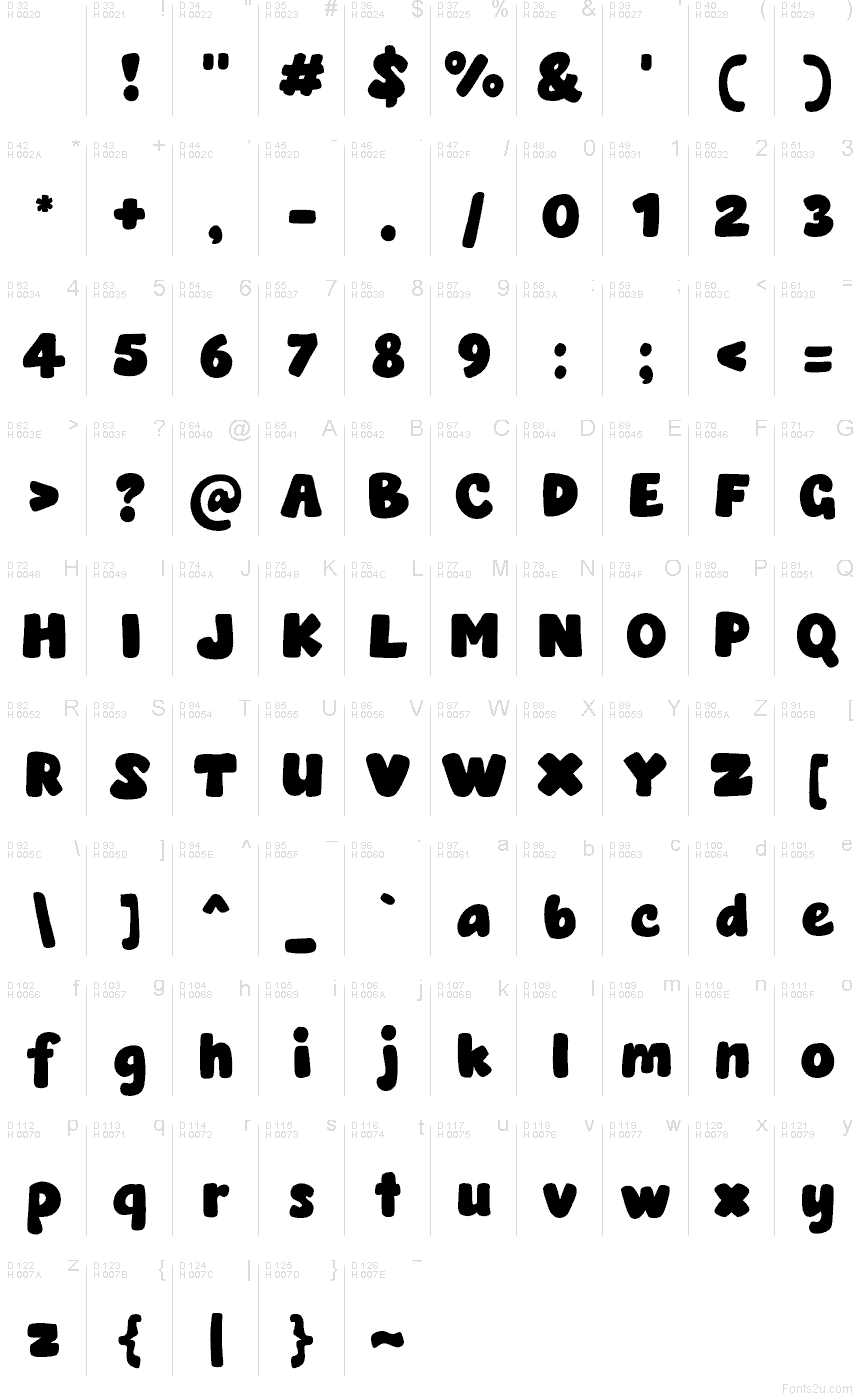
Marshi Sans
Marshi Sans od Origin Type je bezplatné komiksové písmo, ktoré sa vyznačuje zaoblenými tvarmi pripomínajúcimi bubliny a mäkkými rohmi, vďaka čomu pôsobí ako ručne kreslené a má priateľský rytmus. Písmená sú usporiadané vzdušne a neformálne a široké krivky zaisťujú, že celý vzhľad zostáva uvoľnený a prístupný, namiesto ostrých alebo mechanických hrán.
Marshi Sans skvele funguje v detských knihách, na plagátoch, pohľadniciach, v menu kaviarní, logotypoch aj grafike na sociálne siete, pretože jeho zaoblené tvary prinášajú veselý tón bez straty štruktúry. Toto bezplatné písmo sa hodí aj na etikety obalov a označenia podujatí, keď hľadáte komiksový rukopisný štýl, ktorý pôsobí vrelou a bezprostrednou atmosférou.